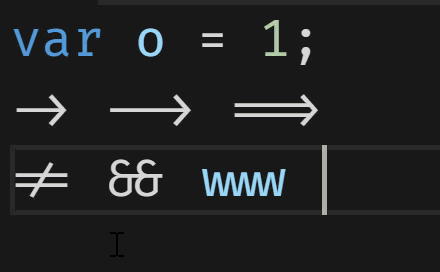
Monospace sans mit Unterlaenge fuer "f"
ich suche den Namen der Schrift im angehaengten Screenshot.
Allerdings wird jetzt leider eine andere Schriftart fuer die Code Beispiele verwendet.
Eine Whatthefont Suche gibt keine Schrift mit f-Unterlaenge; ebensowenig Fontsquirrel, Whatfontis, und Fontspring.
Dank Mono.
Mono sei Dank :-)
In Stereo wäre ff ja auch eine Ligatur! ;-)
Apropos ... "Delightful ligatures" werden angekündigt, aber wohl nicht gezeigt? Oder gucke ich heute nur mono?
"It comes with a few ligatures for the most common coding operators" … was auch immer das heißen mag.
Die automatische Ersetzung von --> zu → beispielsweise. Oder != zu ≠.
Ah, danke. Aber sind das Ligaturen? Oder ist das nur im übertragenen Sinn gemeint?
Aus Bleisetzer-Sicht sicherlich nicht, aber ich vermute mal, dass es sich um die Smartfont-Technologie GSUB oder LIGA handelt. Aber genaueres wird Dir @catfonts erklären können 🙂
Und es ist wirklich clever gemacht!
if (a ≠ b)
ist einfacher zu lesen als
if (a != b)
aber da ja nur im Editor gezeigt wird, während im Text ja tatsächlich != steht, ist der Code weiterhin korrekt. Ganz großes Coder-Kino! :biglove: (Wir kriegen ja sonst nicht so viel fürs Auge.)
Hier hab ich eine Erläuterung gefunden:
Das sind schon die Ersetzungen, die Phoibos gemeint hat.
Stimmt, dazu gab es vor zwei Jahren doch eine recht leidenschaftliche Debatte sowohl in der Programmierer- als auch in der Typoszene (z. B. “Q: Ligatures in programming fonts? A: Hell no” als Replik auf den erwähnten Hanselman-Beitrag). Mittlerweile scheint sich das normalisiert zu haben und die Dagegen-Fraktion ist etwas leiser geworden, auch wenn jene weiterhin eher bei den Designern angesiedelt ist und die Befürworter sich vermehrt unter den Programmierern finden.